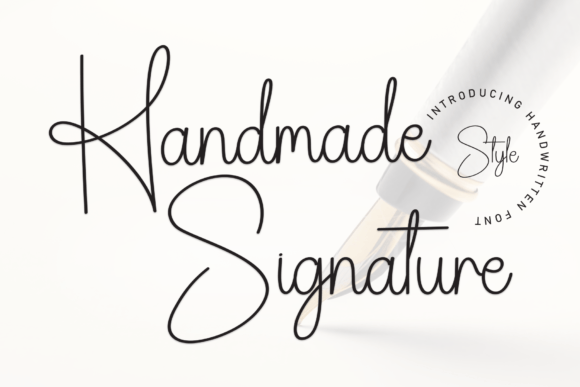
Handmade Signature
適切なデザイン要素を見つけるのは難しい場合がありますが、Handmade Signatureは作品を即座に引き立てる優れたコレクションを提供します。
POD(オンデマンド印刷)製品、結婚式の招待状、またはソーシャルメディアのグラフィックを作成している場合でも、Handmade Signatureは理想的です。